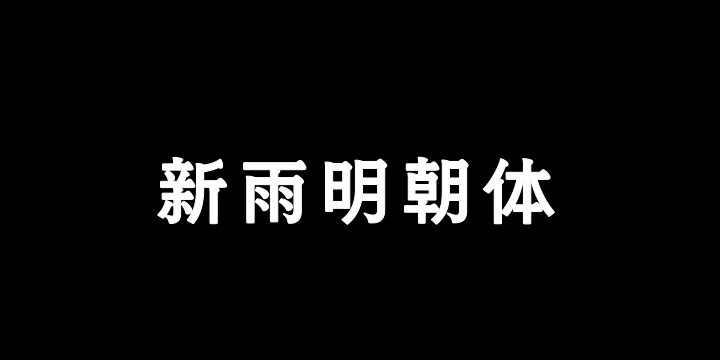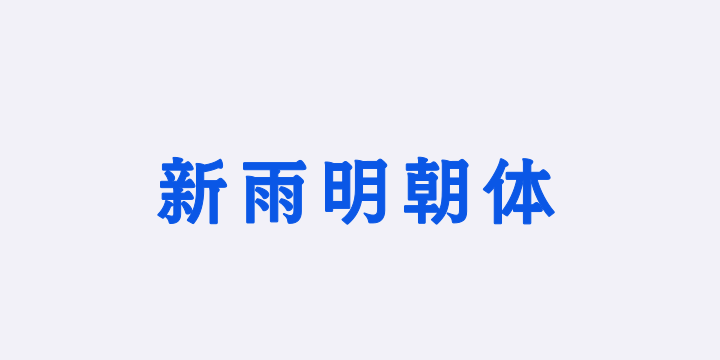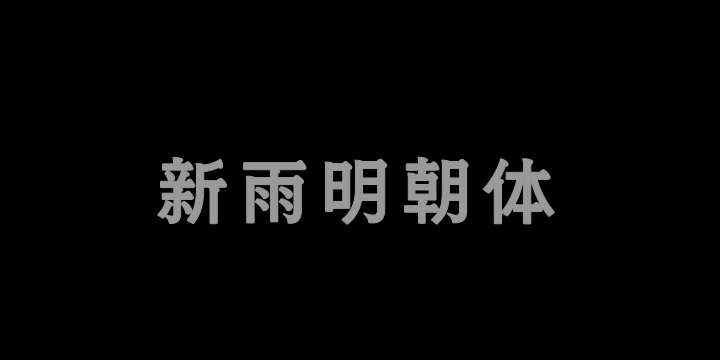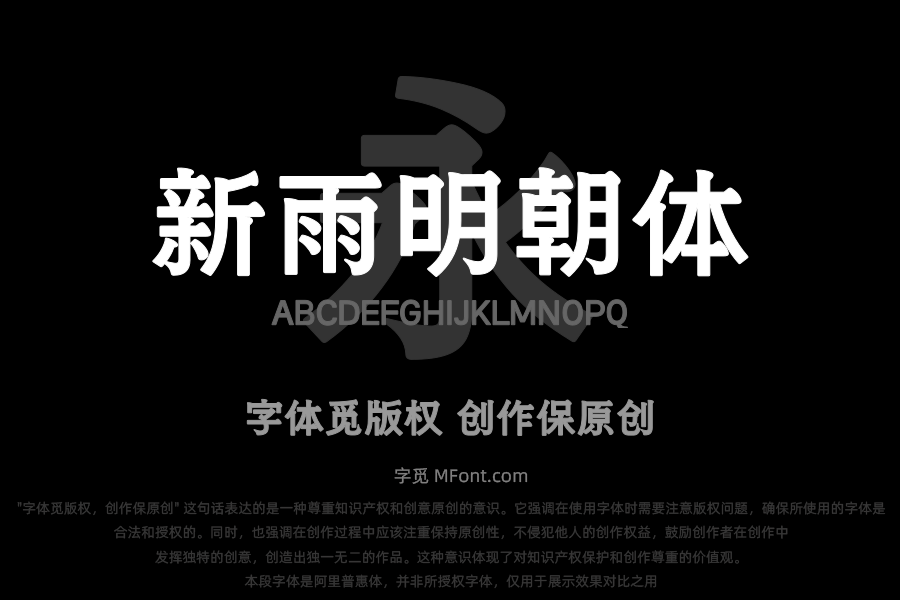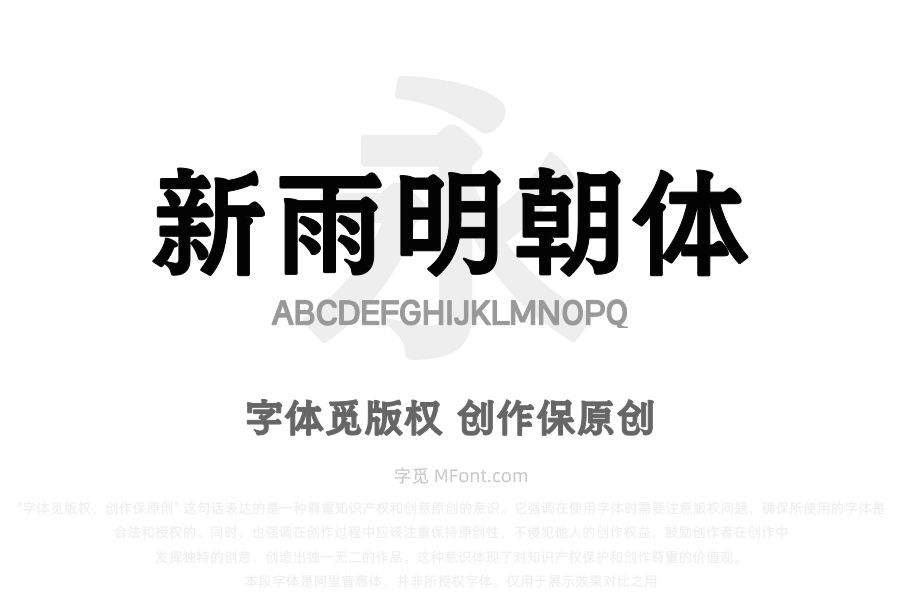
也字工厂新雨明朝体 By 也字工厂 商用字体
字体全名: 也字工厂新雨明朝体
铸字厂: 也字工厂
设计师: 也字工厂
字体简介: 也字工厂新雨明朝体,由「也字工厂」团队耗时1年多打造的一款精品专业字,“新雨明朝”一词,取自《山居秋暝》诗中的新雨意境,雨过天晴,万物焕新,寓意着事与物的转变和更新。恰如这套字体,根植于传统宋体端正与优雅,又融入了现代黑体的锐利与力量,二者平衡取进之间亦是「也字工厂」做字态度的前进--温柔又不失锋芒,传统中拥抱创新。